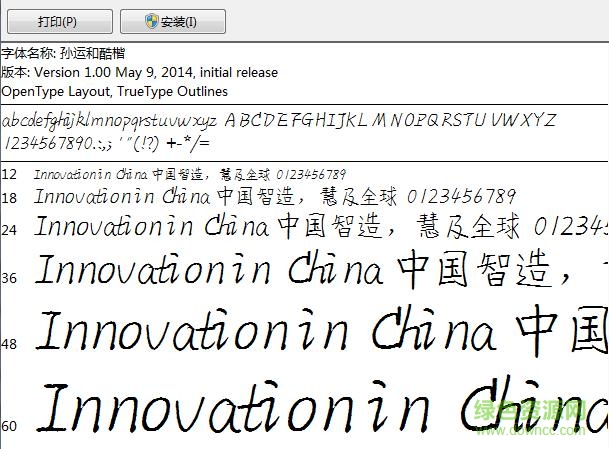
孫運(yùn)和酷楷是一款根據(jù)楷體制作而來(lái)的手寫(xiě)字體,非常簡(jiǎn)潔實(shí)用,美術(shù)設(shè)計(jì)、文字排版等方面都可以使用,有需要用到各種字體進(jìn)行創(chuàng)作的朋友不妨下載使用!
孫運(yùn)和酷楷是一款手寫(xiě)的楷體字體,具有非常鮮明的手寫(xiě)風(fēng)格,其行筆流利,起收分明,筆筆堅(jiān)實(shí)又富彈性,字體結(jié)構(gòu)清晰規(guī)范,非常有趣,適合廣告設(shè)計(jì)、藝術(shù)設(shè)計(jì)。